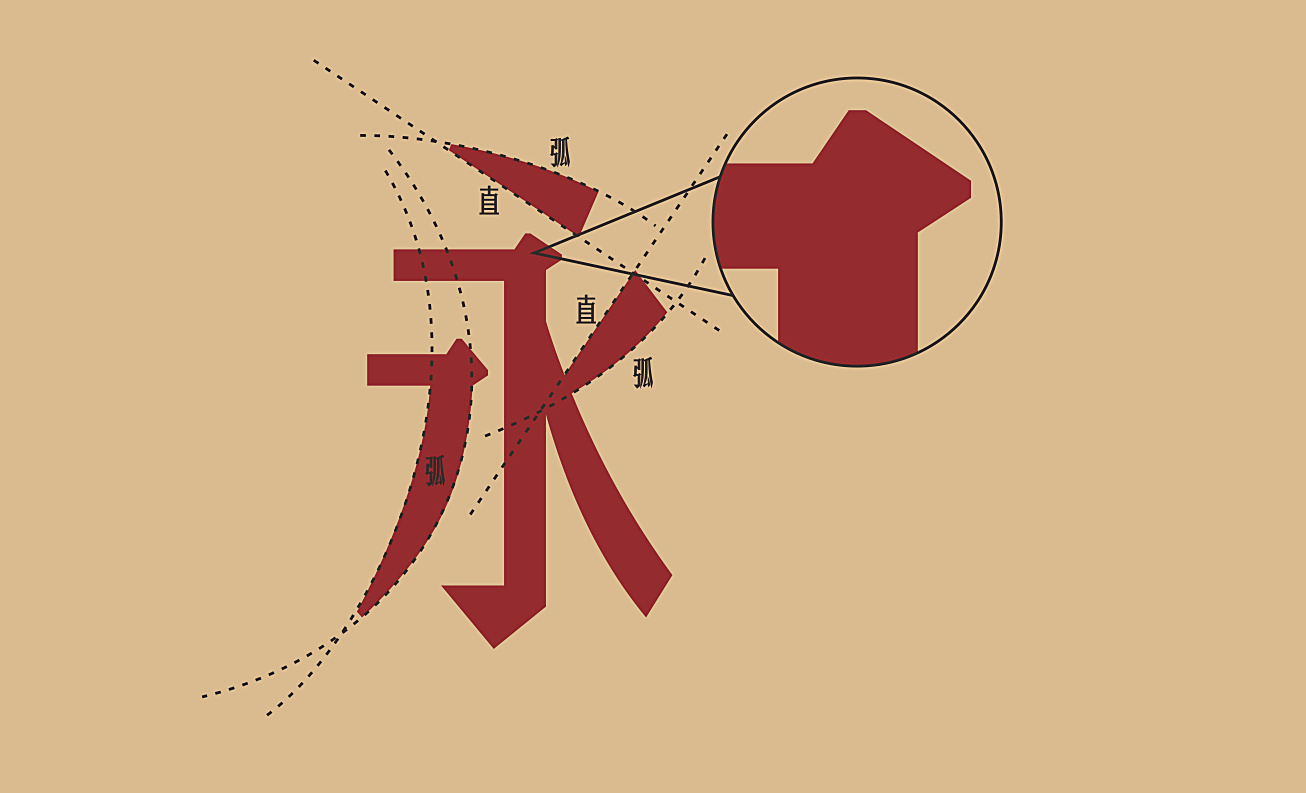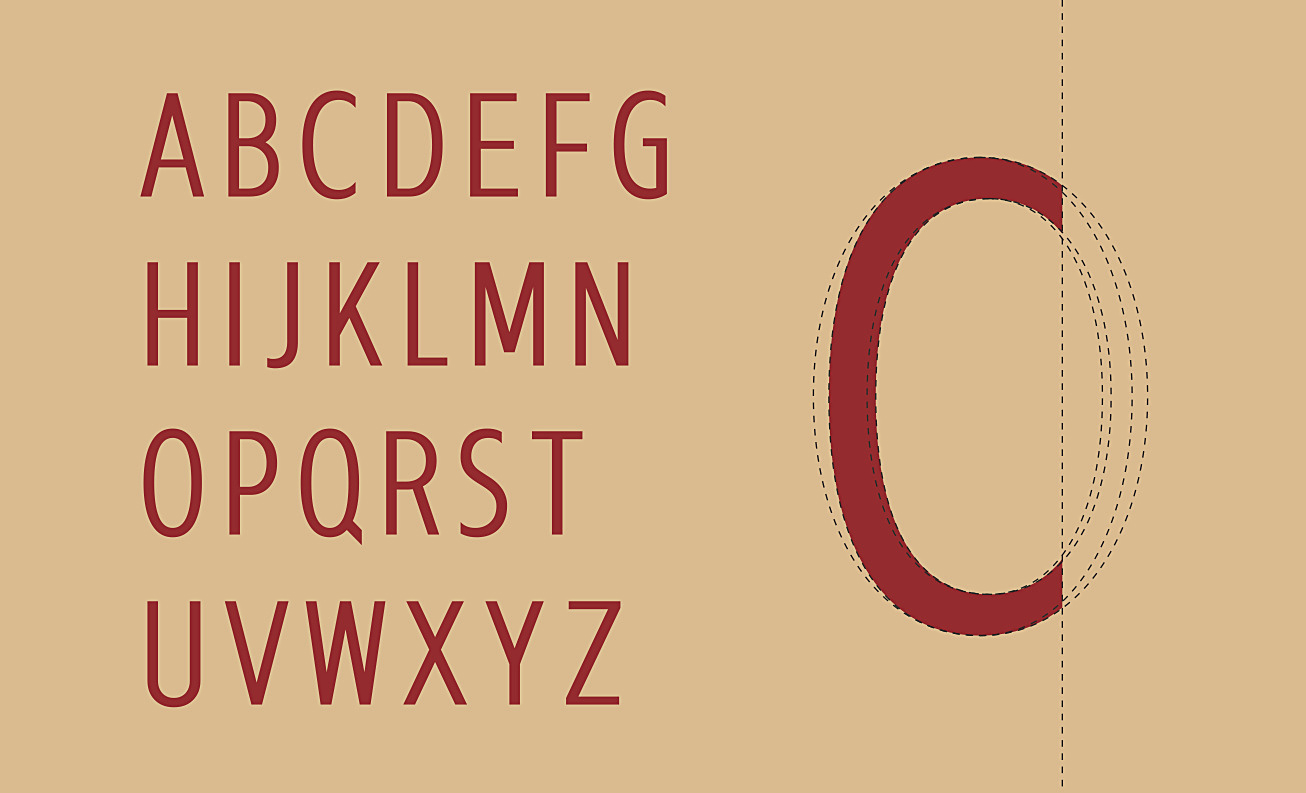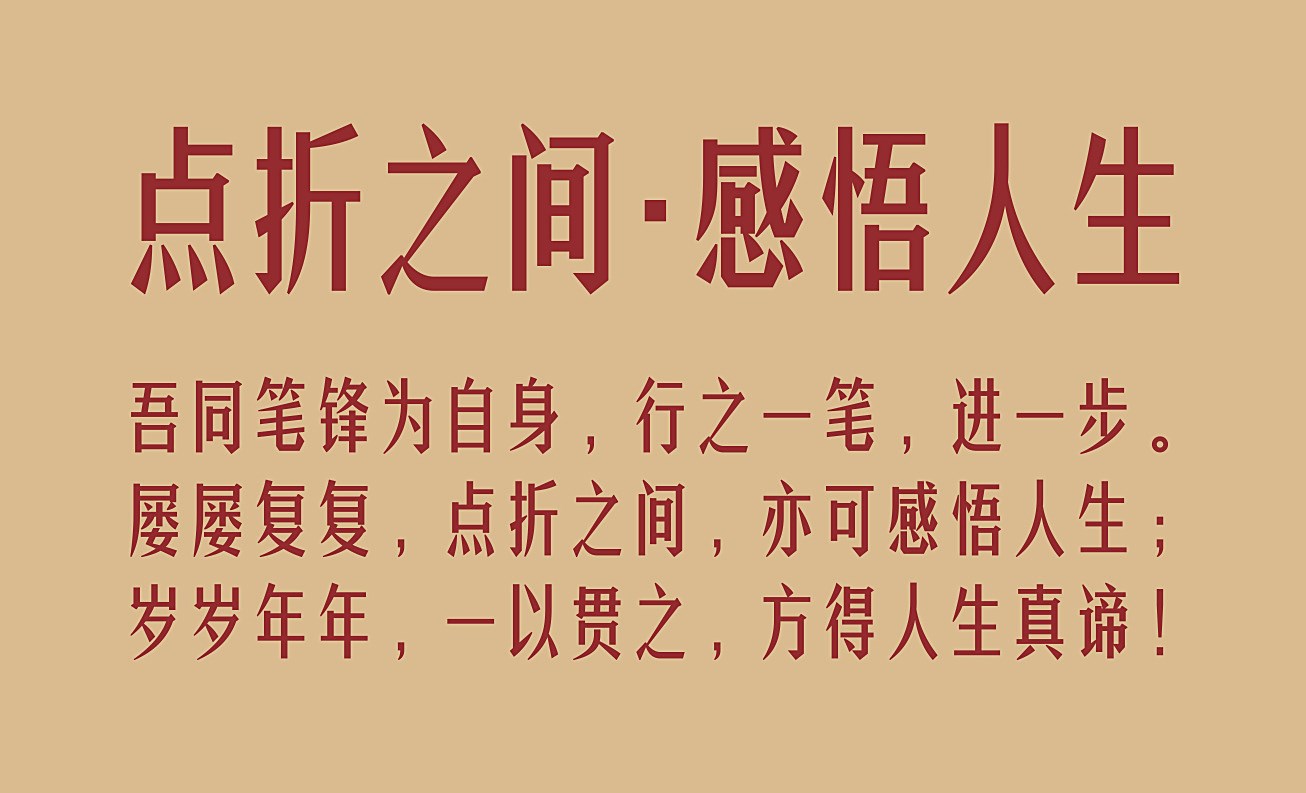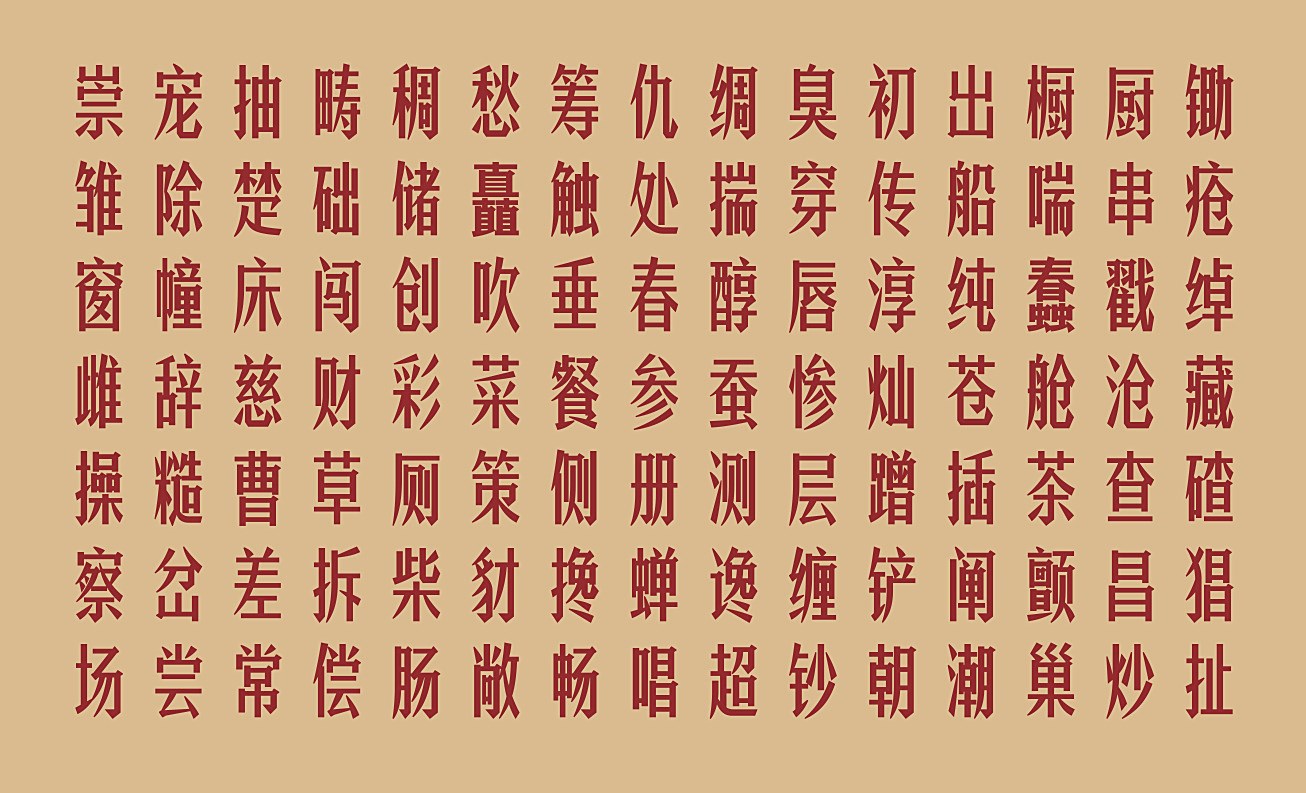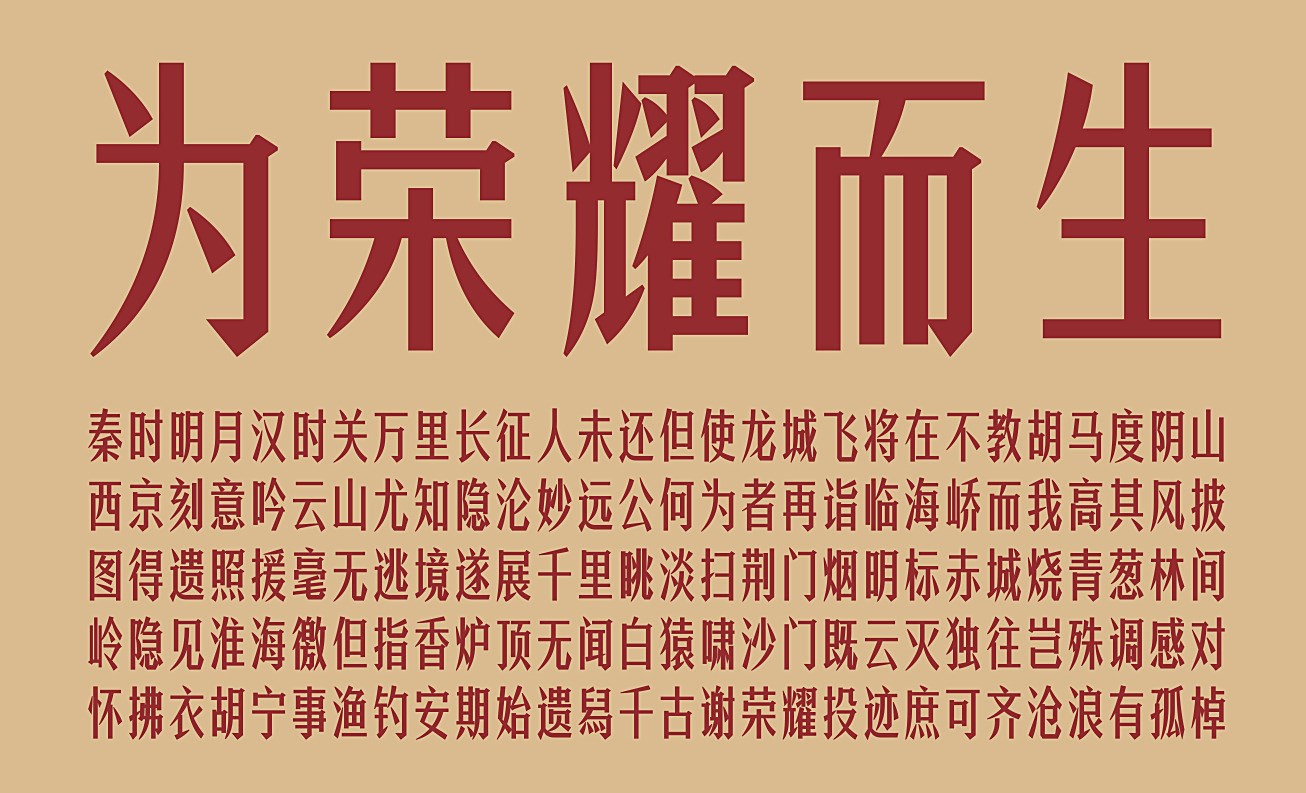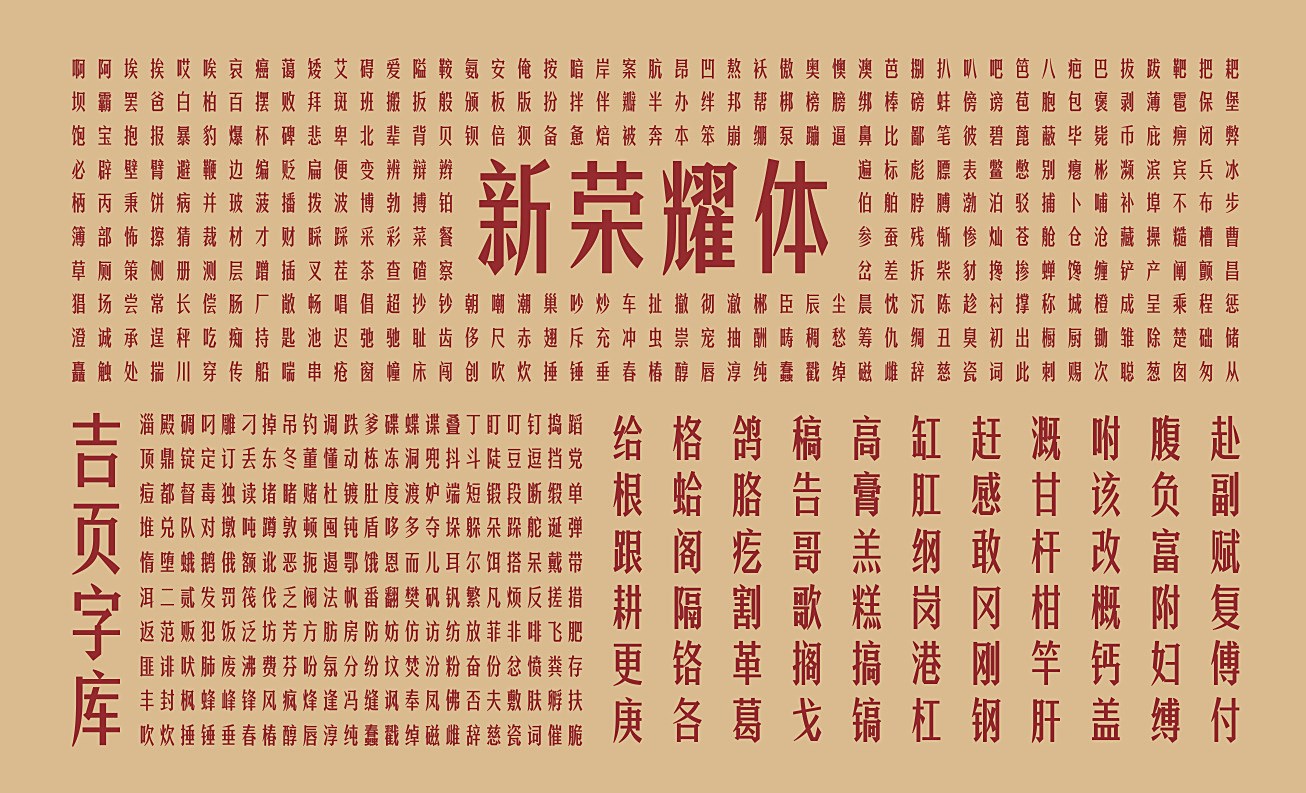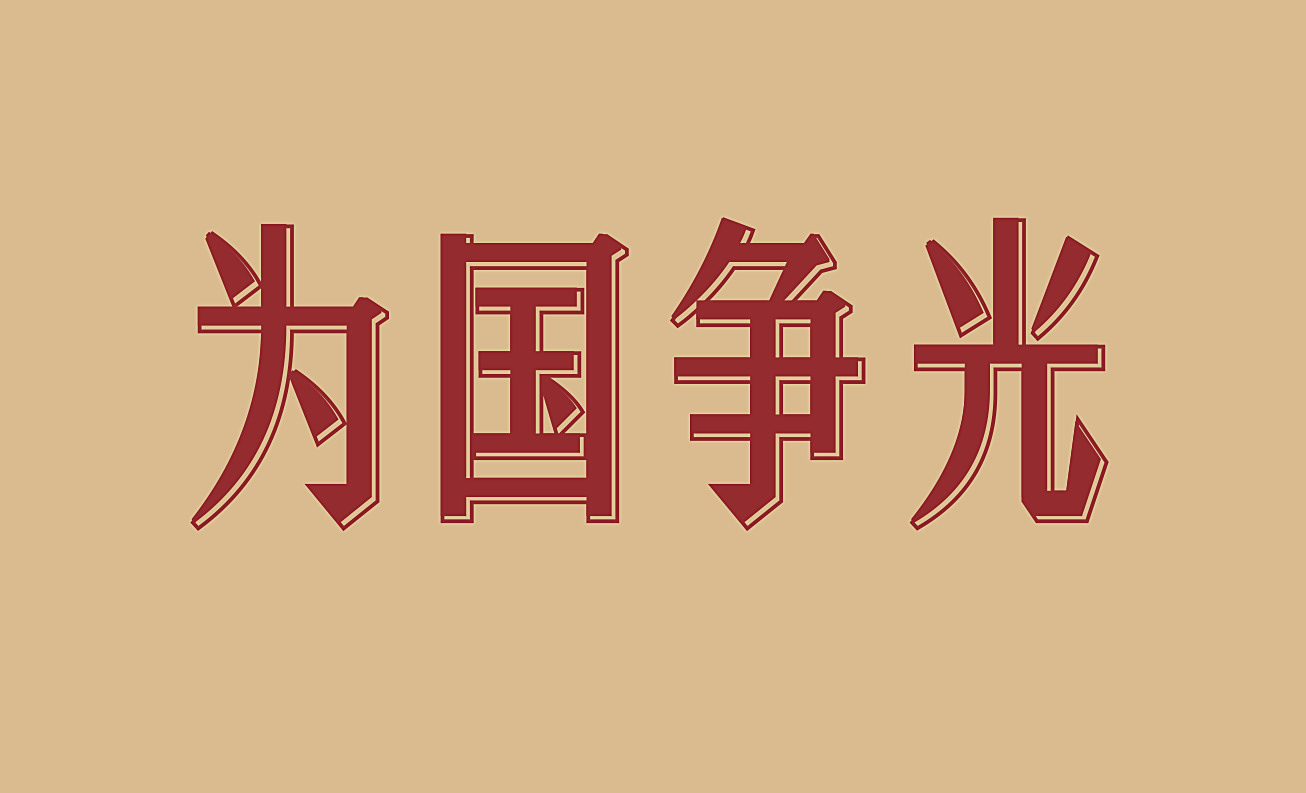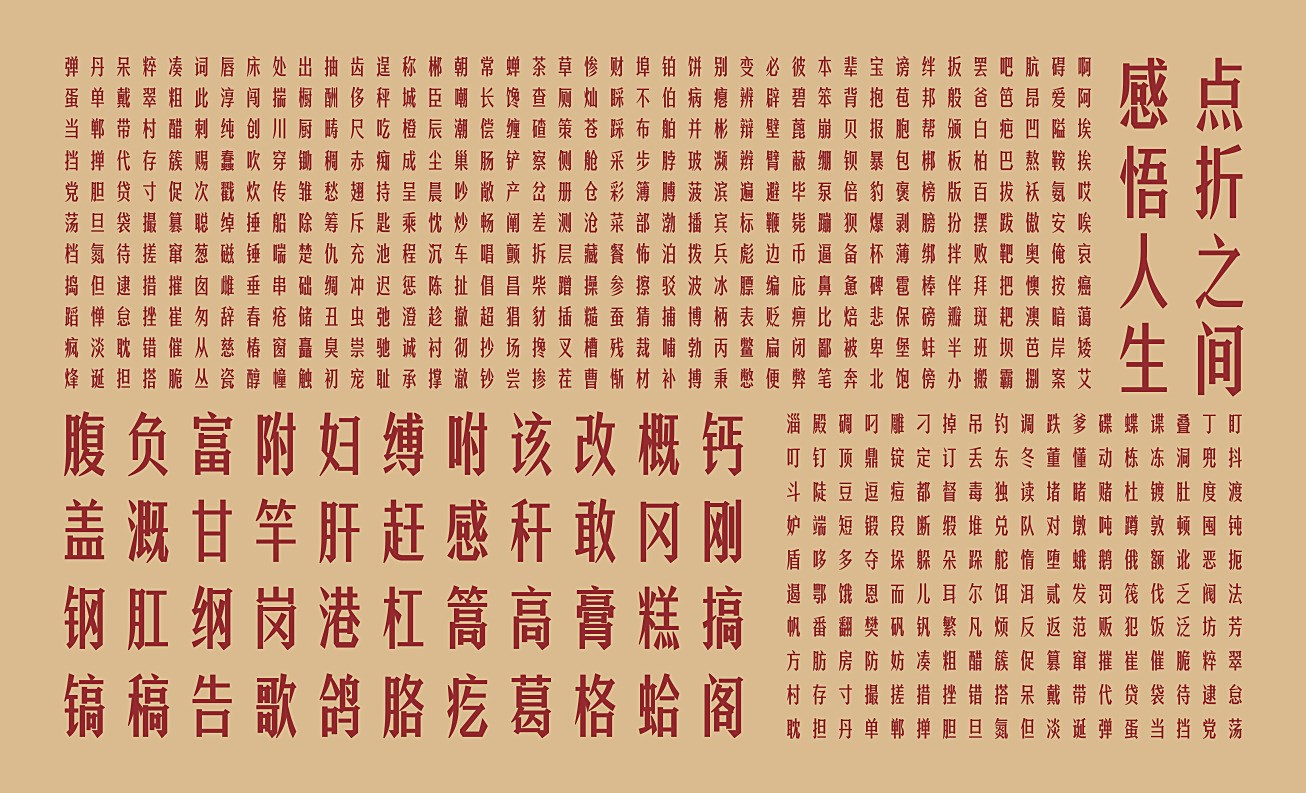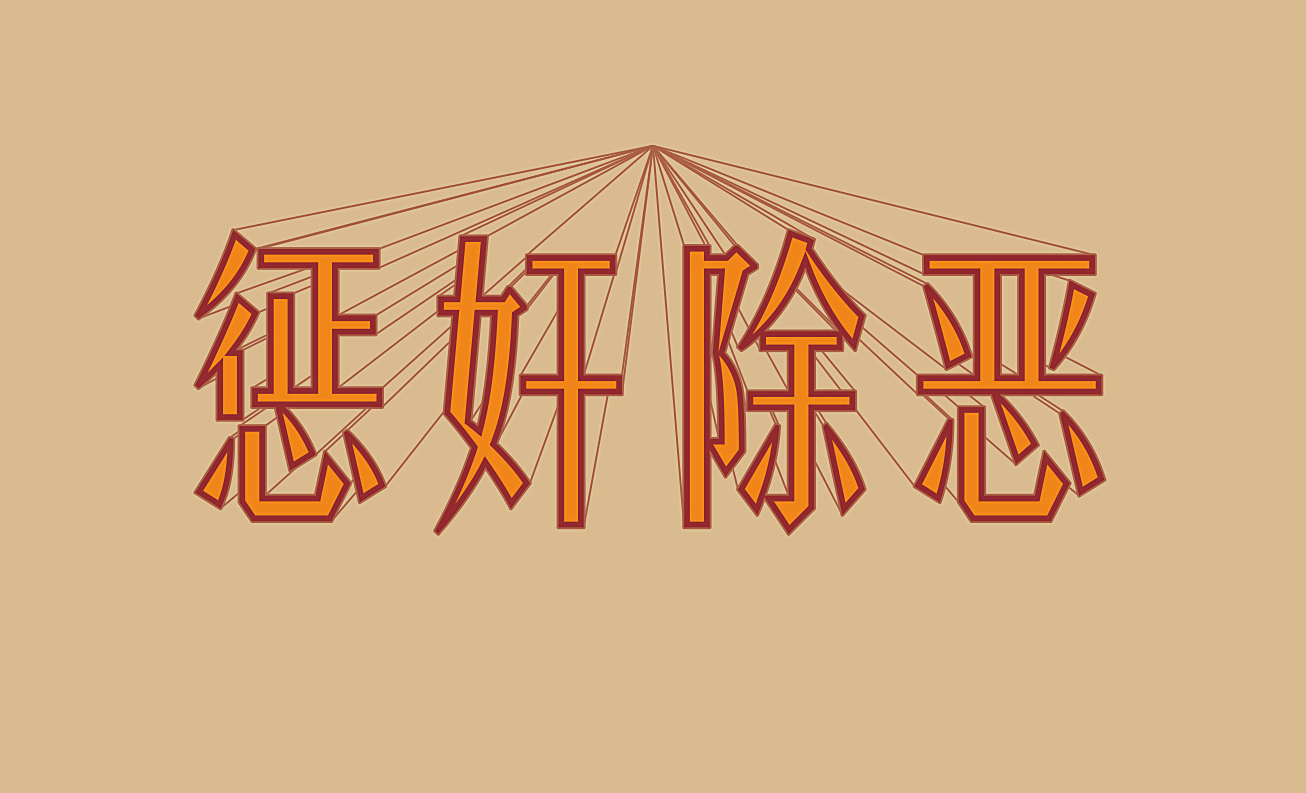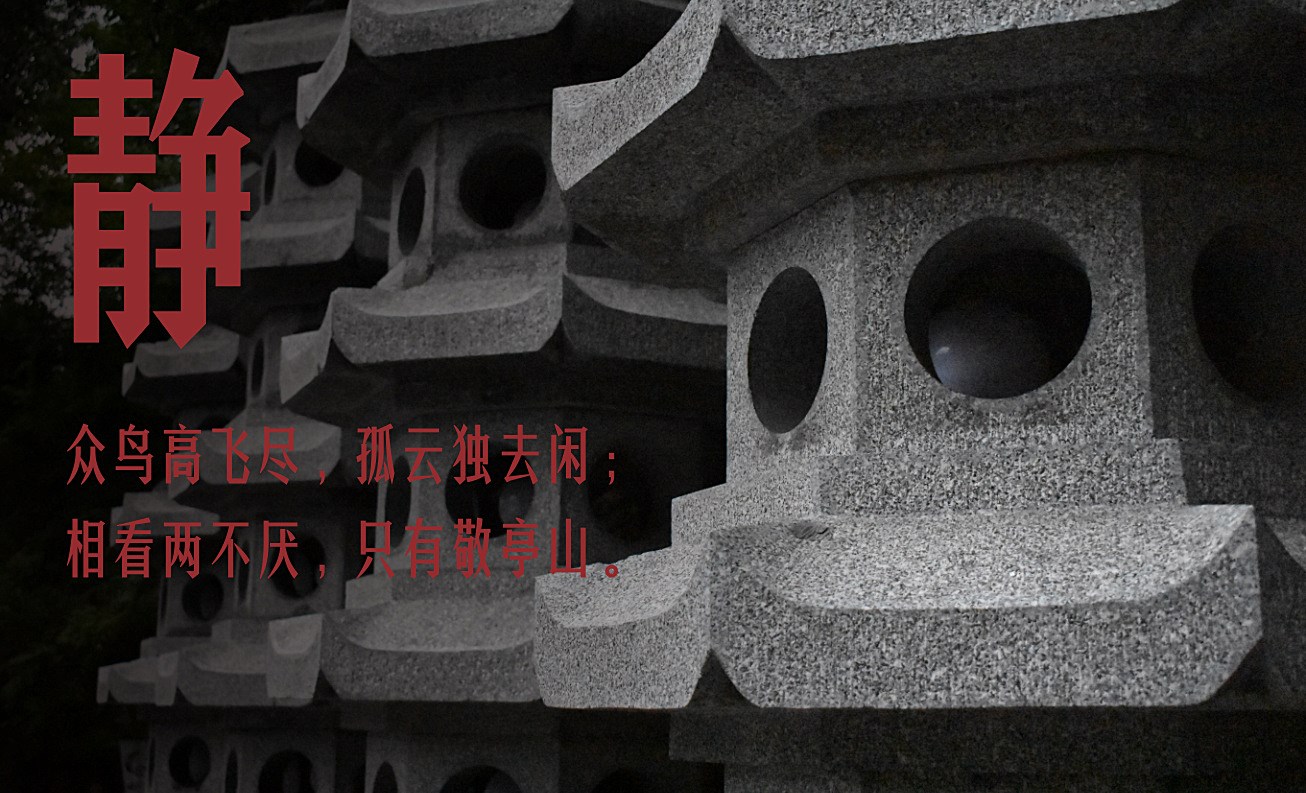
吉页新荣耀体上线了
吉页新荣耀体简在GB2312的基础上增加了148个汉字,共计6911个汉字,大小写西文、数字及常用符号。吉页新荣耀体简是一款新中国初期风格的字体,字体笔划简洁干练,略瘦确有力量,具有历史感。希望广大字友喜欢!
吉页新荣耀体上线了
吉页新荣耀体简在GB2312的基础上增加了148个汉字,共计6911个汉字,大小写西文、数字及常用符号。吉页新荣耀体简是一款新中国初期风格的字体,字体笔划简洁干练,略瘦确有力量,具有历史感。希望广大字友喜欢!
字体横划平直、竖划垂挺,长撇与捺均为弧线,点、短撇、提均由直线与弧线表现,转折处融入宋体风格的装饰。